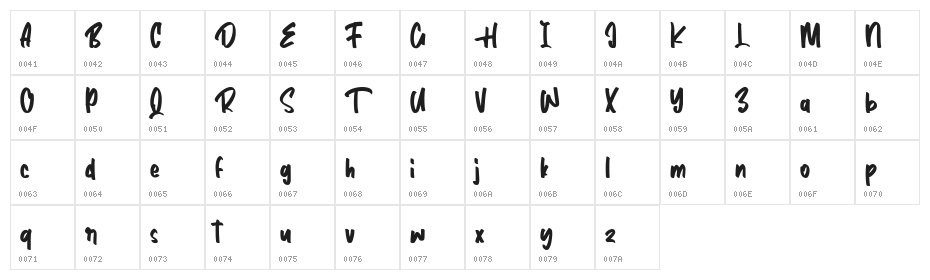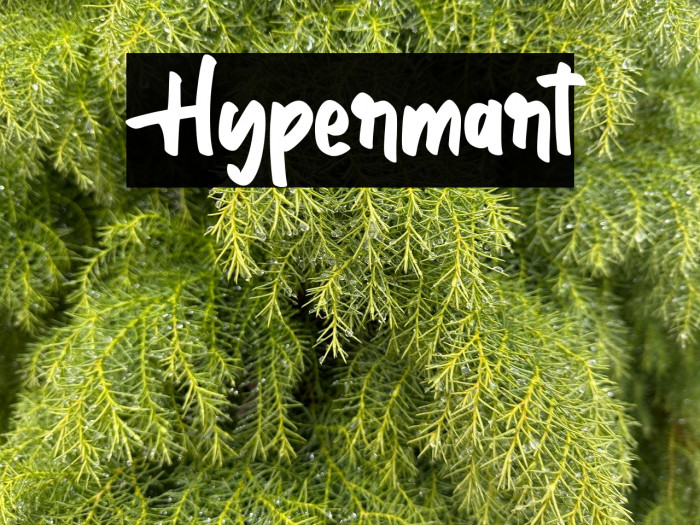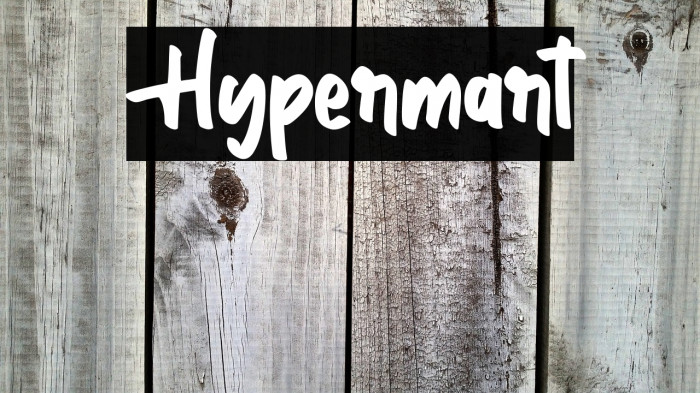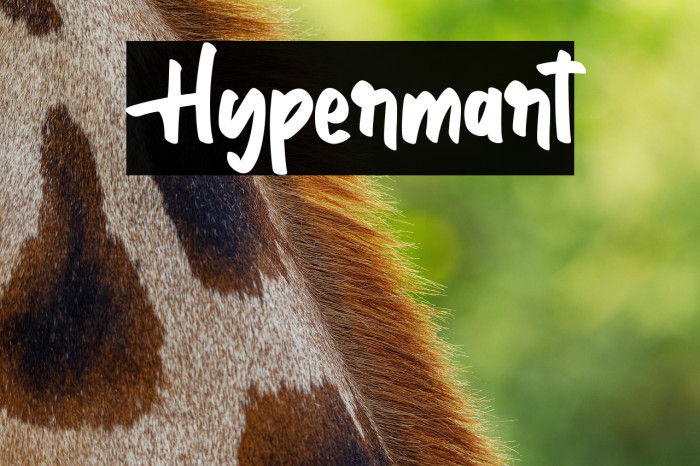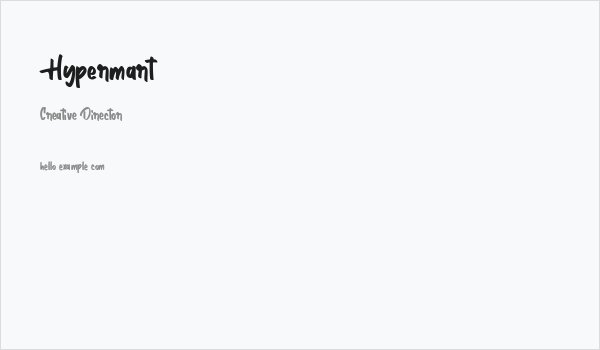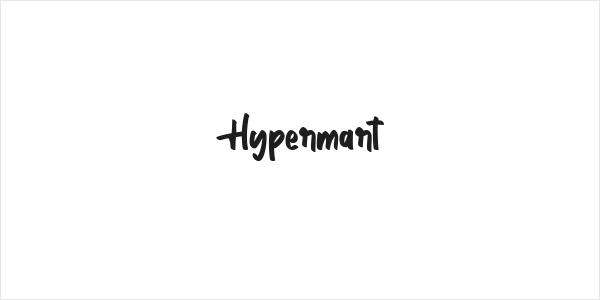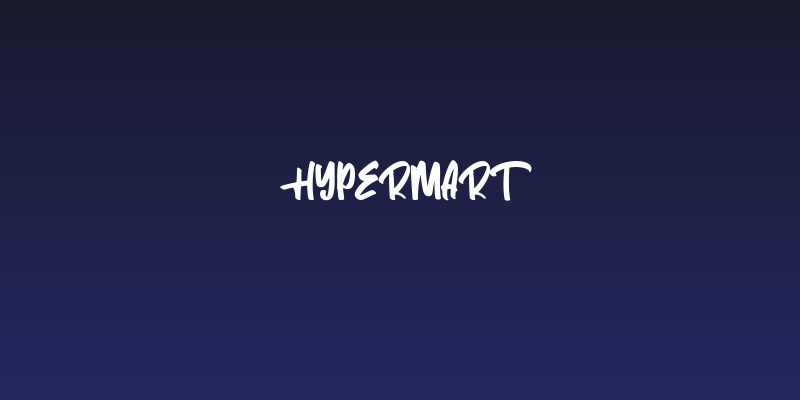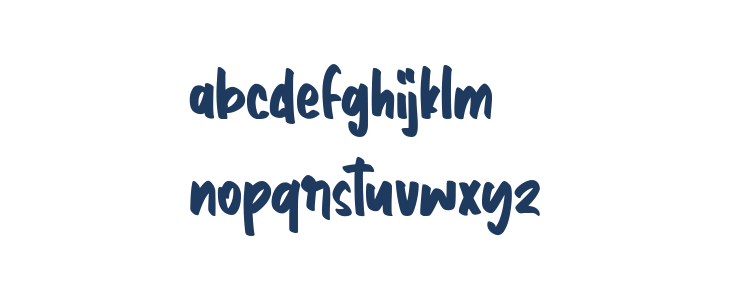
Hypermart Font
| 全体的なスタイル | Playful, Energetic |
| 用途 | Logos, Headlines, Invitations |
| おすすめプロジェクト | Ideal for invitations, greeting cards, creative branding, and playful designs. |